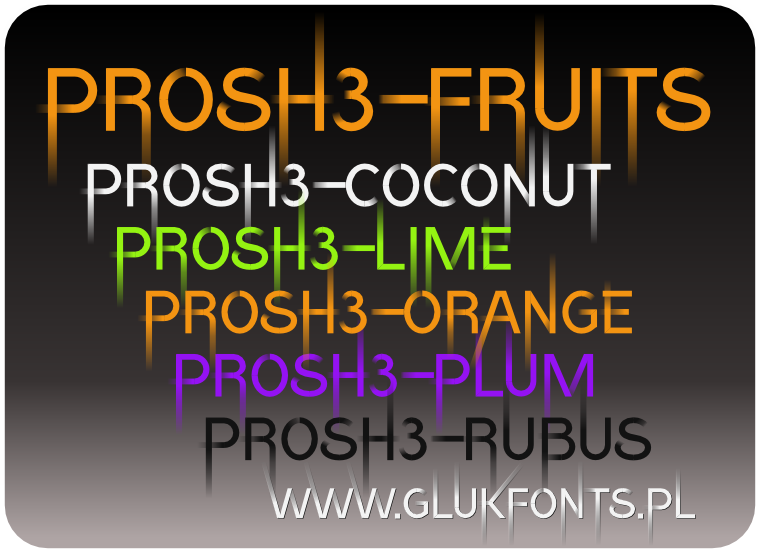
Opentype-SVG font Prosh3-fruits made by gluk
SVGi­nO­pen­Type Prosh3-​fruits: Prosh3-​Orange, Prosh3-​Coconut, Prosh3-​Rubus, Prosh3-​Plum und Prosh3-​Lime sind far­bige Schrif­ten mit ein­ge­bet­te­ten Farb­wer­ten. Open­Type SVG farbe font (SVG-​in-​OT) for­mat ist eine Vor­schlag für mehr­far­bige, vek­tor Schrif­ten und wurde imple­men­tiert in Mozilla Fire­fox (v. >= 26), Micro­soft Edge (v. >= 38.14393), Adobe Photo­shop CC 2017 und Adobe Illus­tra­tor CC 2018.